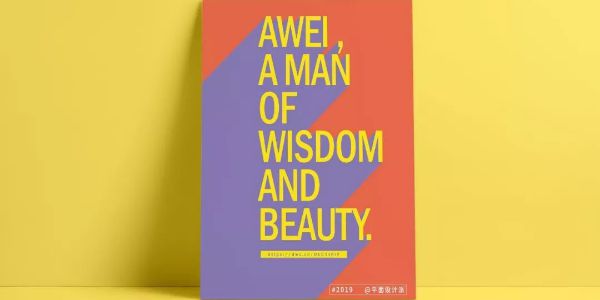
做字体设计时如何做到角度统一,字体设计角度统一的技巧分享
大家好,这期的教程想给大家分享一招设计中经常会运用到的套路----角度统一。角度统一能够让设计看起来非常的高逼格,极具设计感。我们这次要结合几款常用商业案例实操来教大家怎样来做这种类型的设计。
不难看出这类标准字的笔画起笔收笔会比较干净利落,笔画为等粗的无衬线体,笔画角度的统一使其本身具有几何图形美感,整体设计感非常强烈。这类标准字各字面大小一致,结构稳定,一般作为标准字搭配图形元素LOGO使用,也有单独作为LOGO主体使用的情况。
①利用网格搭骨架
“泽岩美術館”偏文艺的命题,下图中我将整体设定为瘦高字型、重心偏高、笔画为较为精致的细线(考虑应用要避免过细);搭骨架(结构)时用钢笔工具、借助网格和字框来进行勾勒,中宫尽量要大撑满字框(笔画往四周外扩),稍微要注意字面内各部件所占字面比例,撇点笔画的角度统一为45°。
②调整字面内各部件比例
上图的骨架我是完全按对齐网格来勾勒的,难免会产生一些不舒服的字面比例,辣么字面比例怎么调?我在下图中运用几款字库字各部件所占比例进行分析,我单独展示“館”字调整,其他我在这里不一一展示,注意的是,做这步不用顾忌网格了,注意字框就行了。
③细节调整
“泽”、“岩”、“術”、“館”的部分笔画处理圆润,调整前整体偏硬朗,处理圆角之后整体柔中带刚,使整体赋予亲和力;“美”、“館”字部分的断开之后,看起来会有一种舒缓、轻松感,前提是注意断开不能影响识别性。
④添加晕染感圆角、排版
我们写毛笔字时,在笔画相交处墨水会晕开,加圆角就是模拟墨水晕开的效果,让整体瞬间更有文艺气息,这种处理方式很常见,也会更营造出主题的文化感。设计同样具有统一角度的英文进行搭配排版。
与前款示例不同的是这类LOGO字体各字面大小不一,具有节奏韵律感;其本身图形感强烈,一般作为LOGO图形主体使用,也有搭配图形元素LOGO使用的情况。
①注意设计目标
家里边几乎都是北欧家居风格的装备,其干净简洁没有浮夸的装饰,“北欧宜品居”是我此次示范的主题。
②搭骨架
搭骨架时注意笔画与笔画之间的间距保持一致,高度根据横笔的数量做延伸,形成错落感,字面宽度一致,这次示范我选择下对齐方式进行排版,或者你也可以选择上对齐方式,这样看起来不会乱。还是老方法,结构控制不好的童鞋还是乖乖利用网格和字框勾勒,填满字框,注意点撇笔画45°角度统一。
③调整细节
“品”字下方的口字部间距调整一致;笔画扩展之后调整倾斜笔画的切平处理,使整体笔画保持干净。注意“欧”字内交叉笔画要特殊处理,各位客官有空可以尝试两种切平处理方式(水平或垂直切平)。
④搭配英文排版
选择无衬线的英文字体进行搭配,排版完成。是不是很简单,又极具设计感。我果然是一个集美貌与才华于一身的女子。
与前面两款示例不同的是,这类创意海报标题字是为了适应版面而排列,再添加英文、图形元素和辅助文字排版而成,往往作为海报主题而存在,这也是纯文字海报与常规海报不同之处。它适用于偏人文、艺术类海报展示。
①搭骨架
此时此刻正坐在桌前写教程的我,眼前出现了重影,我想大概是老眼昏花,感觉身体被掏空。“错落感——字重影响下的视错觉”主题海报着实应景,起先着手就考虑笔画一定是要干净利落;在搭骨架的时候注意单个复合字也要形成大小对比的节奏感,其与主题相呼应。如下图,同样利用网格进行勾勒,点撇笔画还是一样保持45°角度统一,注意笔画与笔画之间的对齐关系。
②添加细节
眼花时出现的重影刚好能制造一种视错觉上的错落感,如下图我利用几何元素的添加形成一种错落空间感,注意调整“感”字字面空间,保持整体视觉平衡。在之前的教程我有提到过,元素的添加和笔画的处理方式都要有缘由,不知道怎么处理的童鞋可以从参考中找灵感和借鉴,不要单纯想炫技。
③搭配排版
排版时注意保持文字从上至下的视觉流畅性,即笔画对齐,字与字对齐,如下图我做了对齐辅助线。